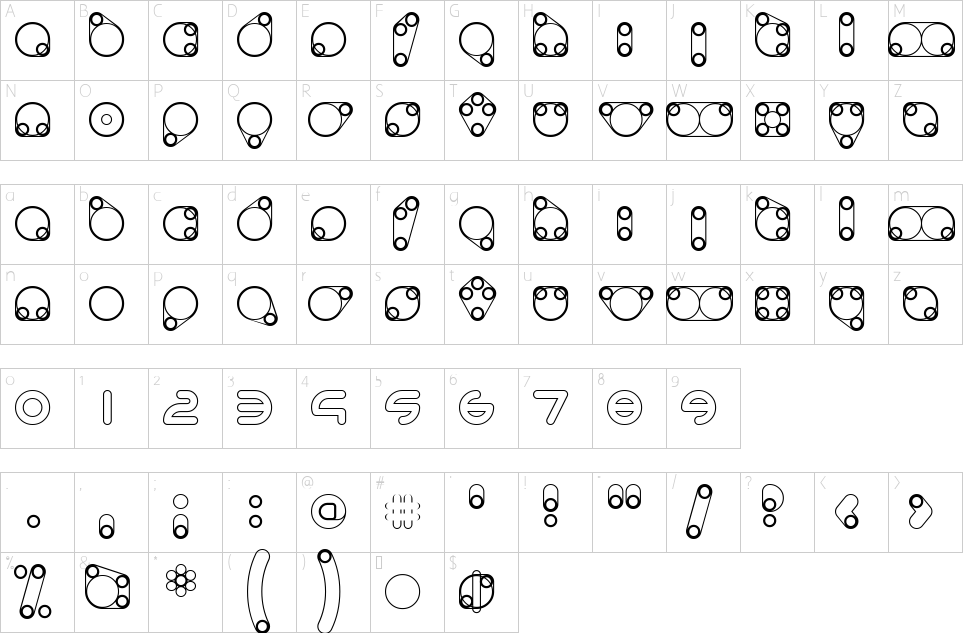
Descubra a Animoto Font, uma elegante e sofisticada fonte que combina perfeitamente com seu design gráfico. Desenvolvida por Adam Rucki, esta fonte é uma escolha inteligente para qualquer projeto que exija uma aparência moderna e profissional. Animoto é conhecida por suas capacidades únicas de montagem de vídeos, mas agora, você também pode adquirir o seu próprio estilo de escrita, adaptado para Windows e Mac. Com seu design minimalista e agradável aos olhos, a Animoto Font é ideal para criar design de websites, editoriais de redes sociais, e qualquer outro projeto que você possa imaginar. Seja um designer, fotógrafo ou profissional de marketing, a Animoto Font é uma fonte grata que pode deixar seu trabalho ainda mais profissional e estiloso. Com apenas 5,157 downloads, ela é uma opção sólida para aqueles que desejam adicionar um toque único a suas criações digitais.